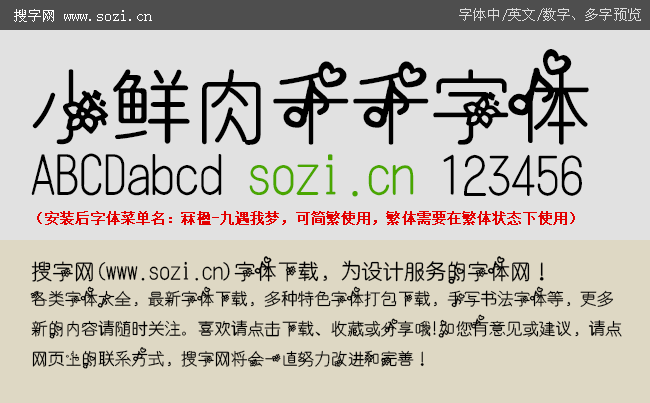
小鮮肉千千字體
搜字網(wǎng)給大家提供一款小鮮肉千千字體手機(jī)中文字體下載。這款手機(jī)字體是以圓體字體為原形,筆畫間嵌入了可愛的卡通花朵與心形圖案。在具備圓字體清晰端正的風(fēng)格同時(shí),卡通味也特別濃,是一款非常可愛的卡通字體,特別適合喜歡手機(jī)字體個(gè)性一些的朋友在手機(jī)上安裝使用。